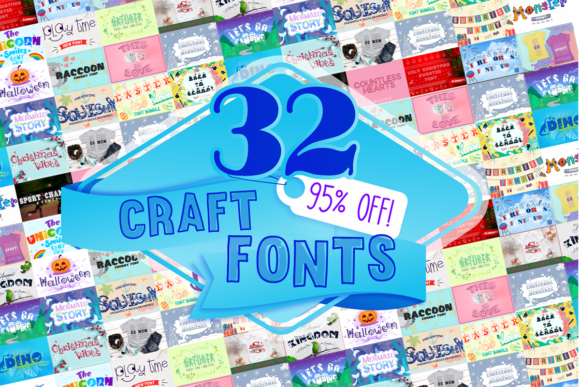
Craft Fonts Bundle
適切なデザイン要素を見つけるのは難しい場合がありますが、Craft Fonts Bundleは作品を即座に引き立てる優れたコレクションを提供します。
POD(オンデマンド印刷)製品、結婚式の招待状、またはソーシャルメディアのグラフィックを作成している場合でも、Craft Fonts Bundleは理想的です。